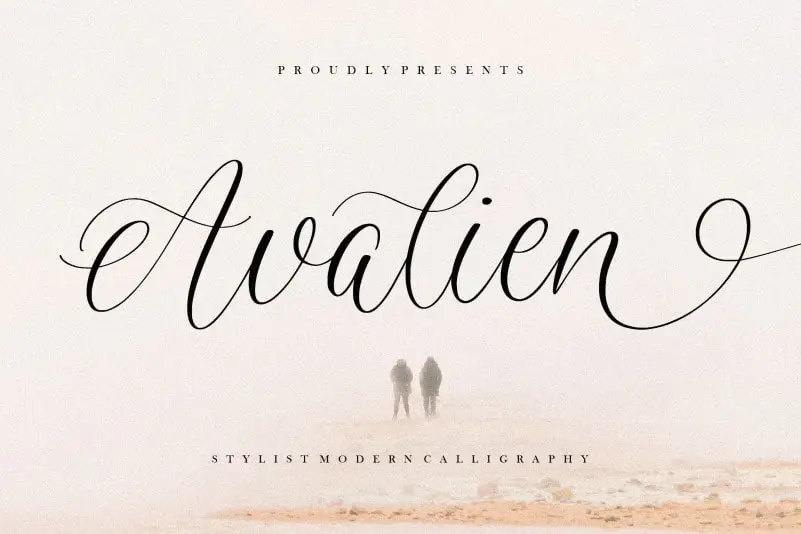
Avalien Calligraphy Font – Download Grátis
Avalien é uma elegante tipografia para cílios que se destaca no seu espaço, perfeitamente adaptada para variedades de aplicativos: desde embalagens de produtos até projetos de marca e publicações de revistas, passando por redes sociais, casamentos ou apenas um suave toque em mensagens em primeiro plano. Com sua delicadeza e estilo único, Avalien pode ser usado para criar expressões lindas que se destacam no seu contexto, seja ele qual for. Ideal tanto para designers de produto quanto para criativos em geral, esta fonte é uma ótima adição ao seu arsenal de ferramentas gráficas.